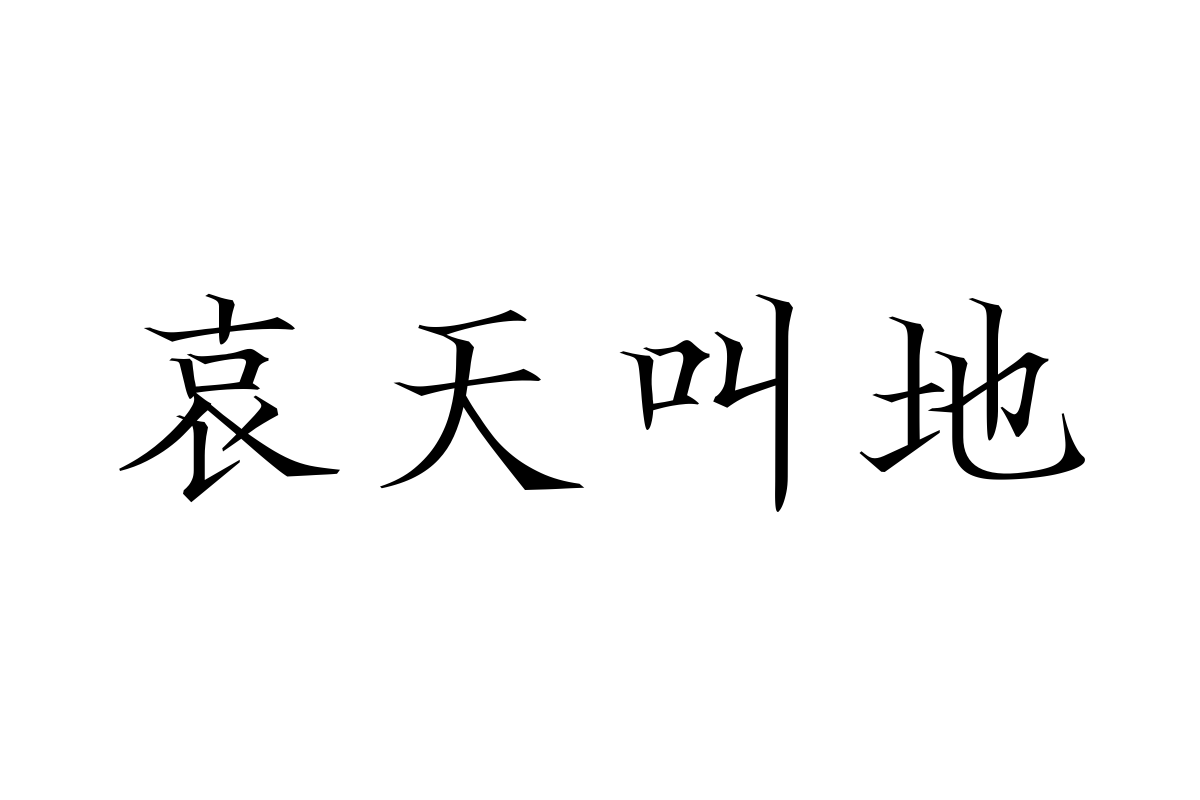
汉仪锐楷字体是一款具有现代感和简洁风格的中文字体,它以其独特的字形结构和流畅的笔画线条而受到广泛欢迎。该字体的设计旨在为用户提供一种清晰、易读且具有美感的视觉体验。
汉仪锐楷字体的特点包括:
1. 字形结构:该字体采用了现代的设计手法,将传统的楷书字形进行了简化和优化,使其更加符合现代人的审美习惯。同时,字体中的字间距和行间距也经过精心设计,使得整体视觉效果更加协调和舒适。
2. 笔画线条:汉仪锐楷字体的笔画线条流畅自然,没有过多的修饰和装饰,给人一种简约而不失优雅的感觉。这种设计风格使得字体在各种应用场景中都能展现出良好的适应性和表现力。
3. 适用性:无论是用于印刷品、网页设计还是其他数字媒体,汉仪锐楷字体都能提供良好的可读性和美观度。其现代感的设计使得字体在各种场合下都能展现出独特的魅力。
总之,汉仪锐楷字体是一款具有现代感和简洁风格的中文字体,它以其独特的字形结构和流畅的笔画线条赢得了广大用户的喜爱。无论是用于商业广告、书籍出版还是其他设计项目,汉仪锐楷字体都能为您的作品增添一份独特的魅力。